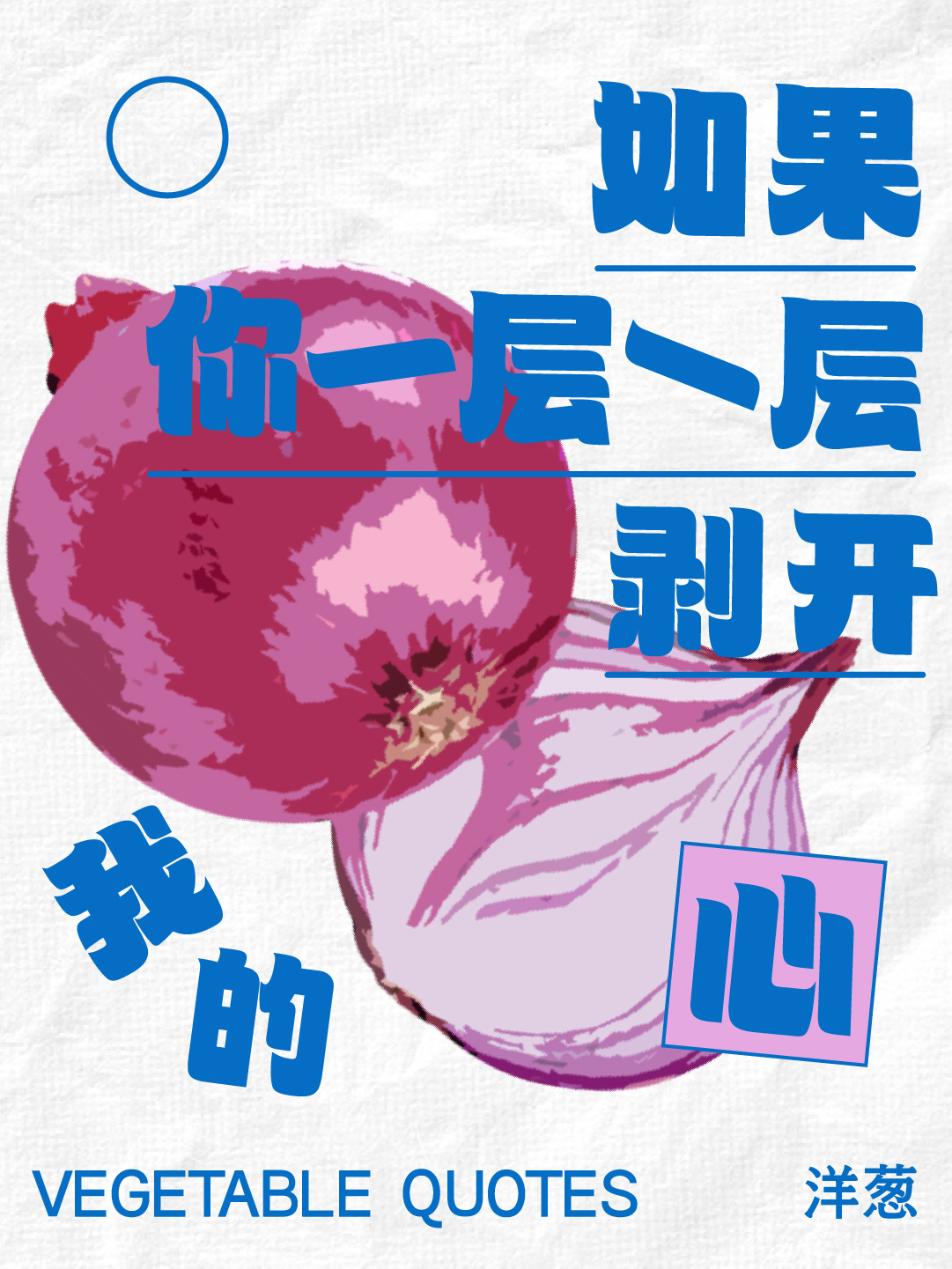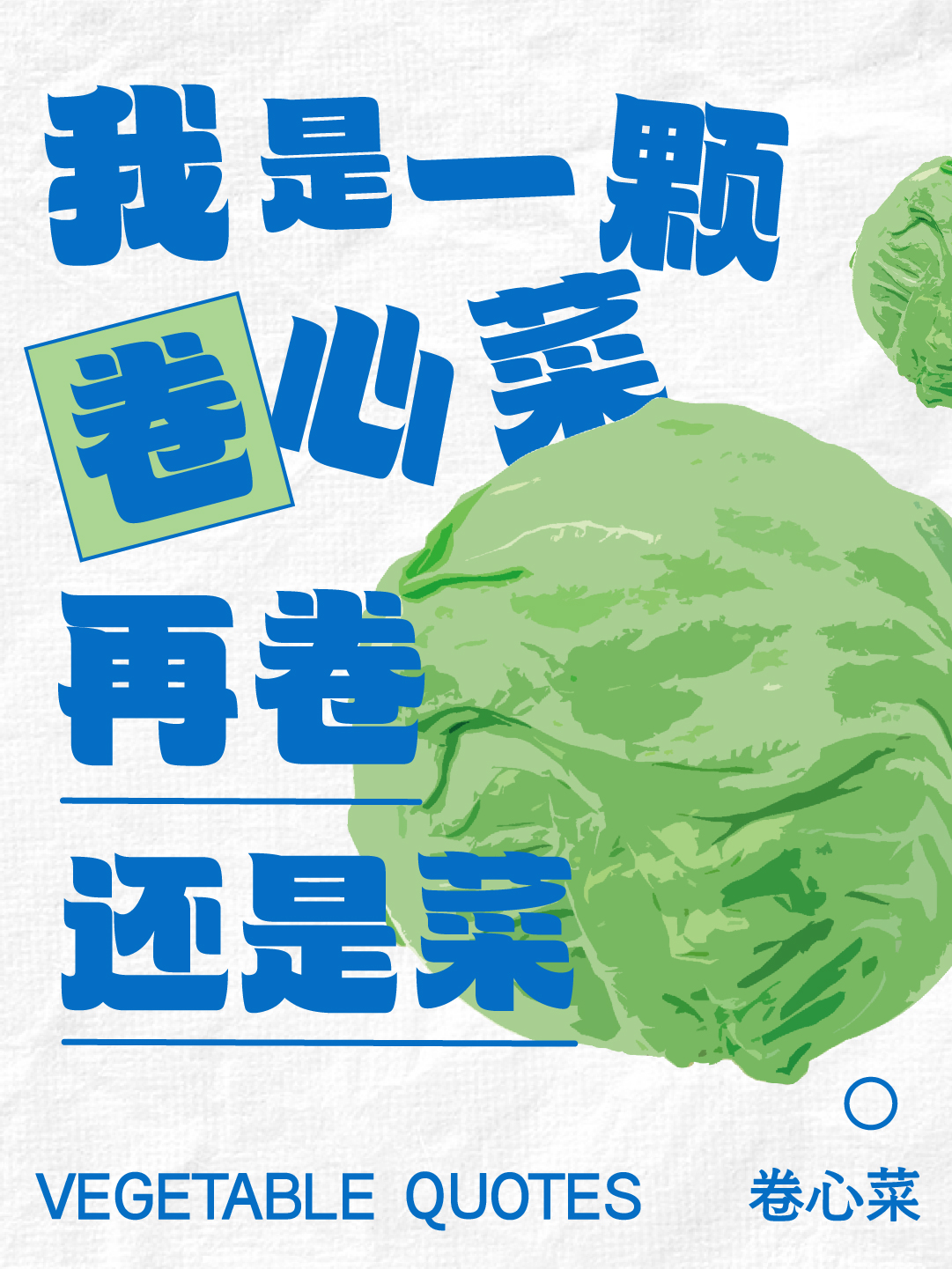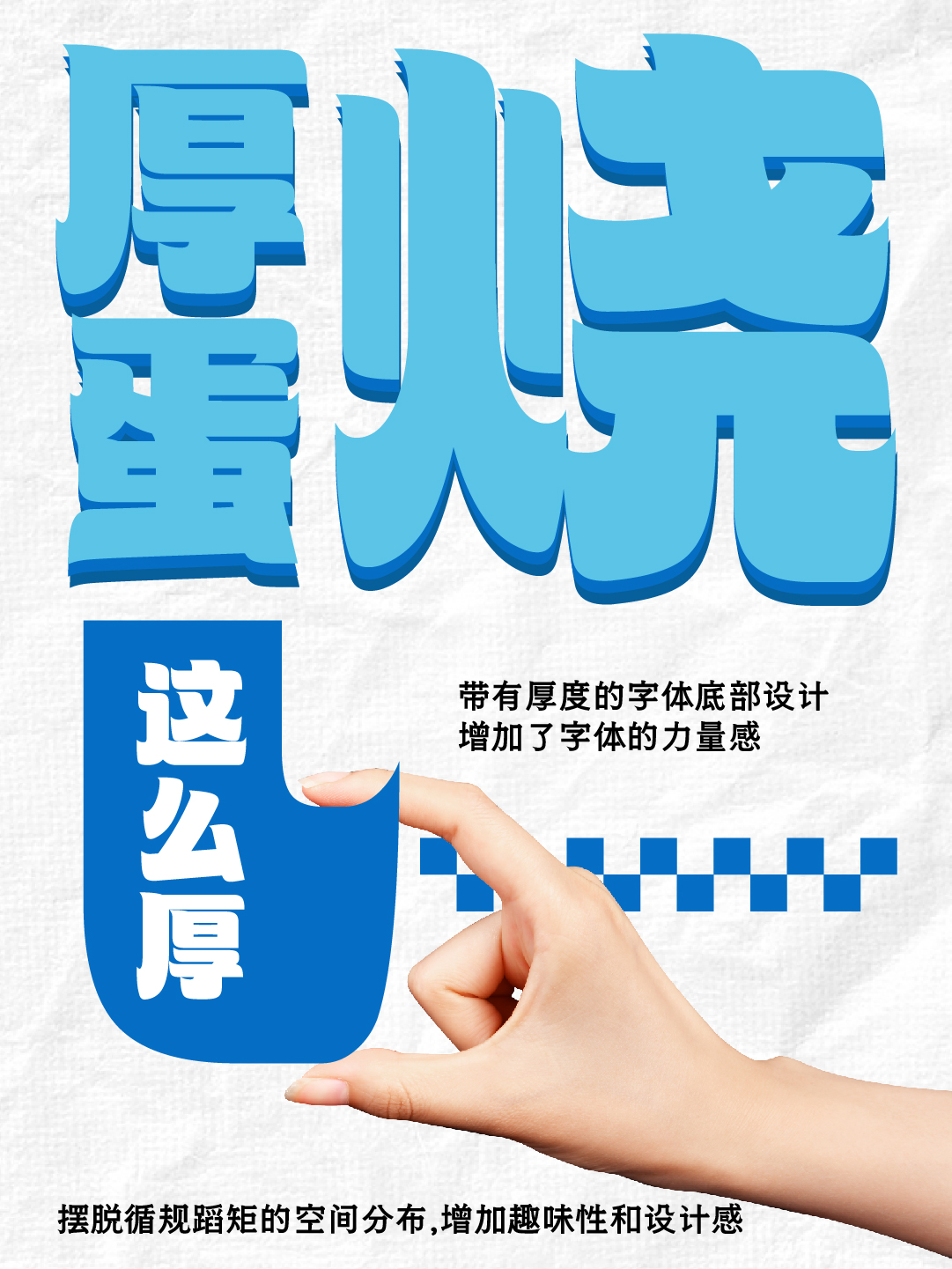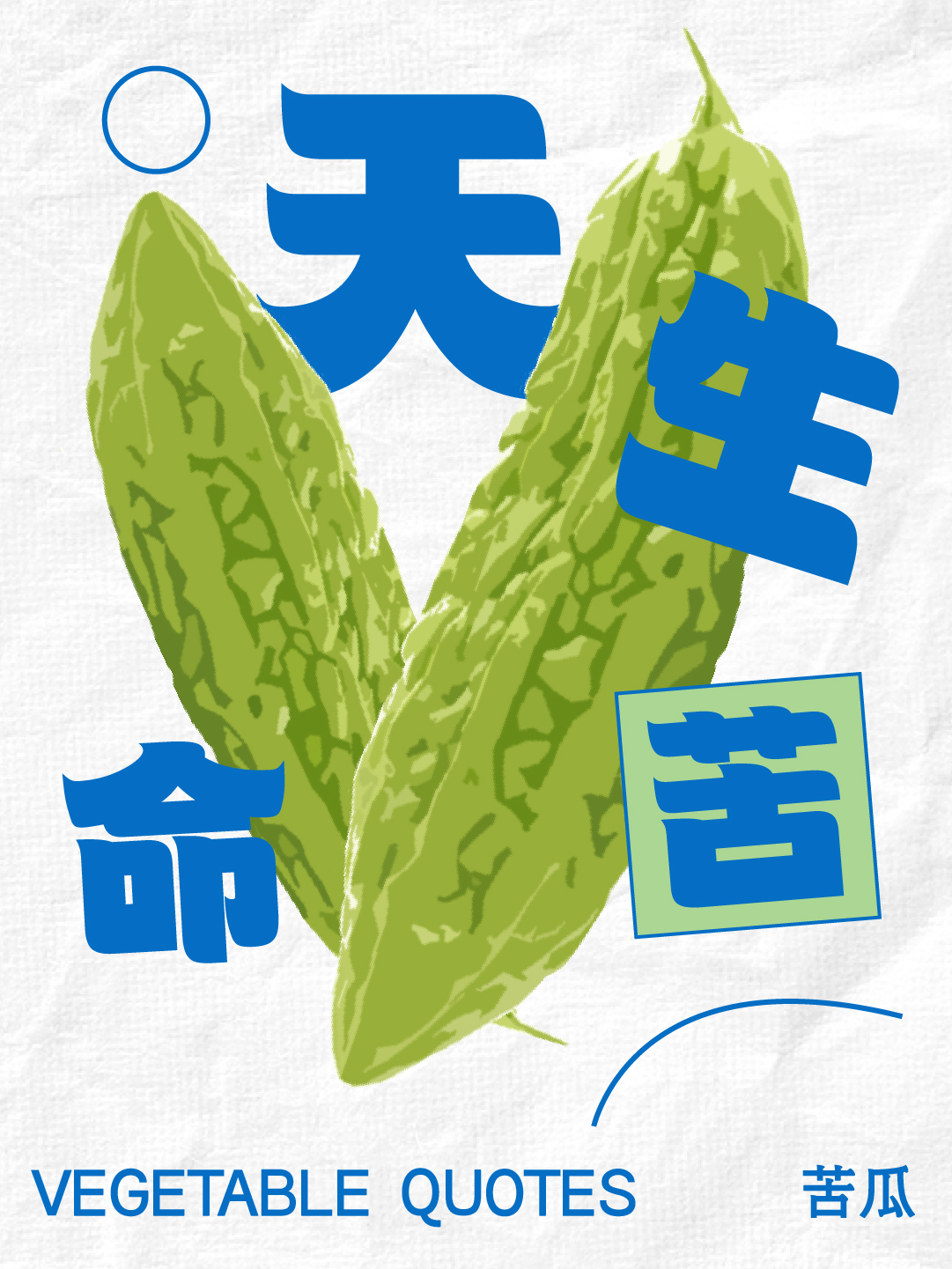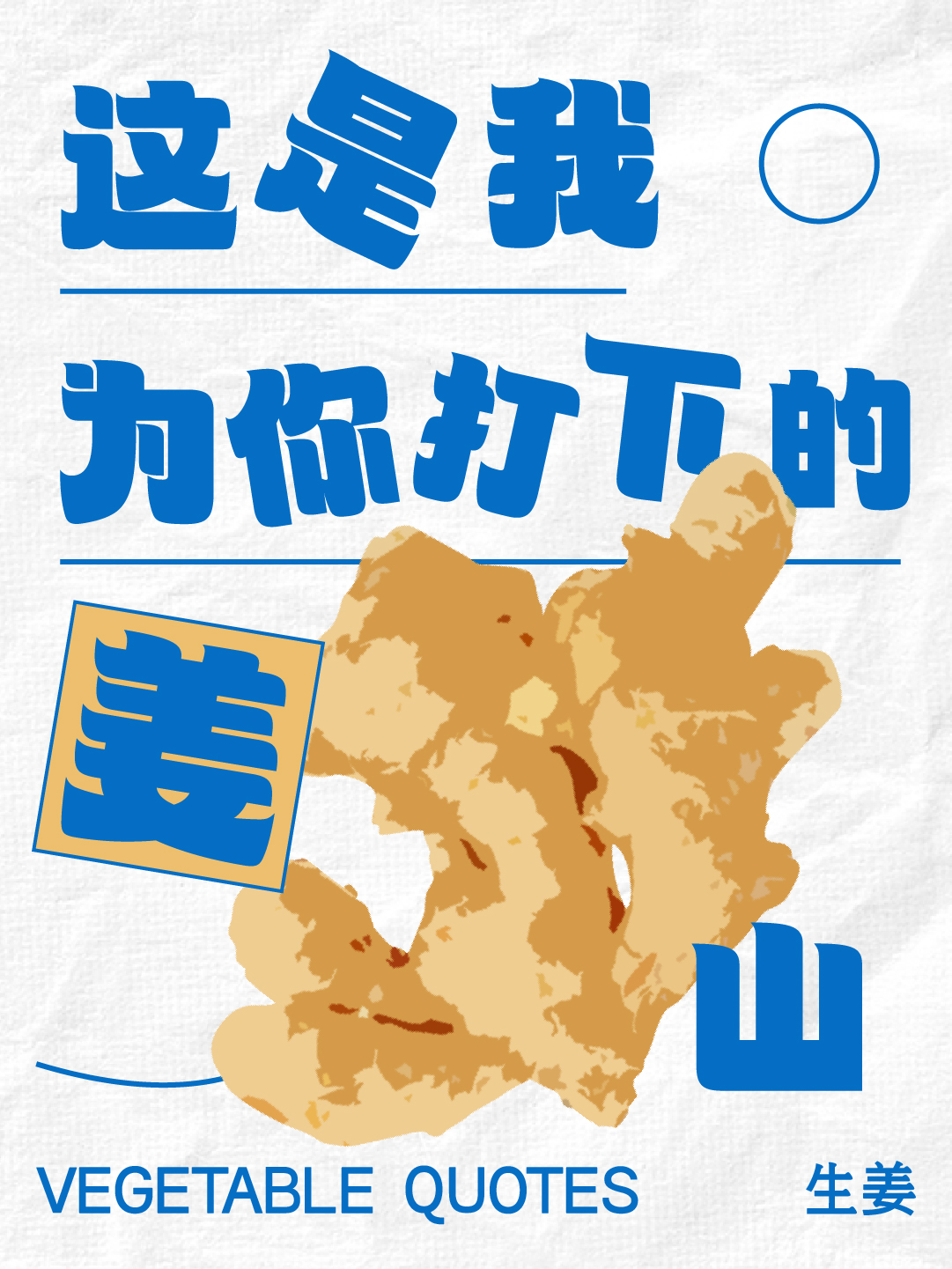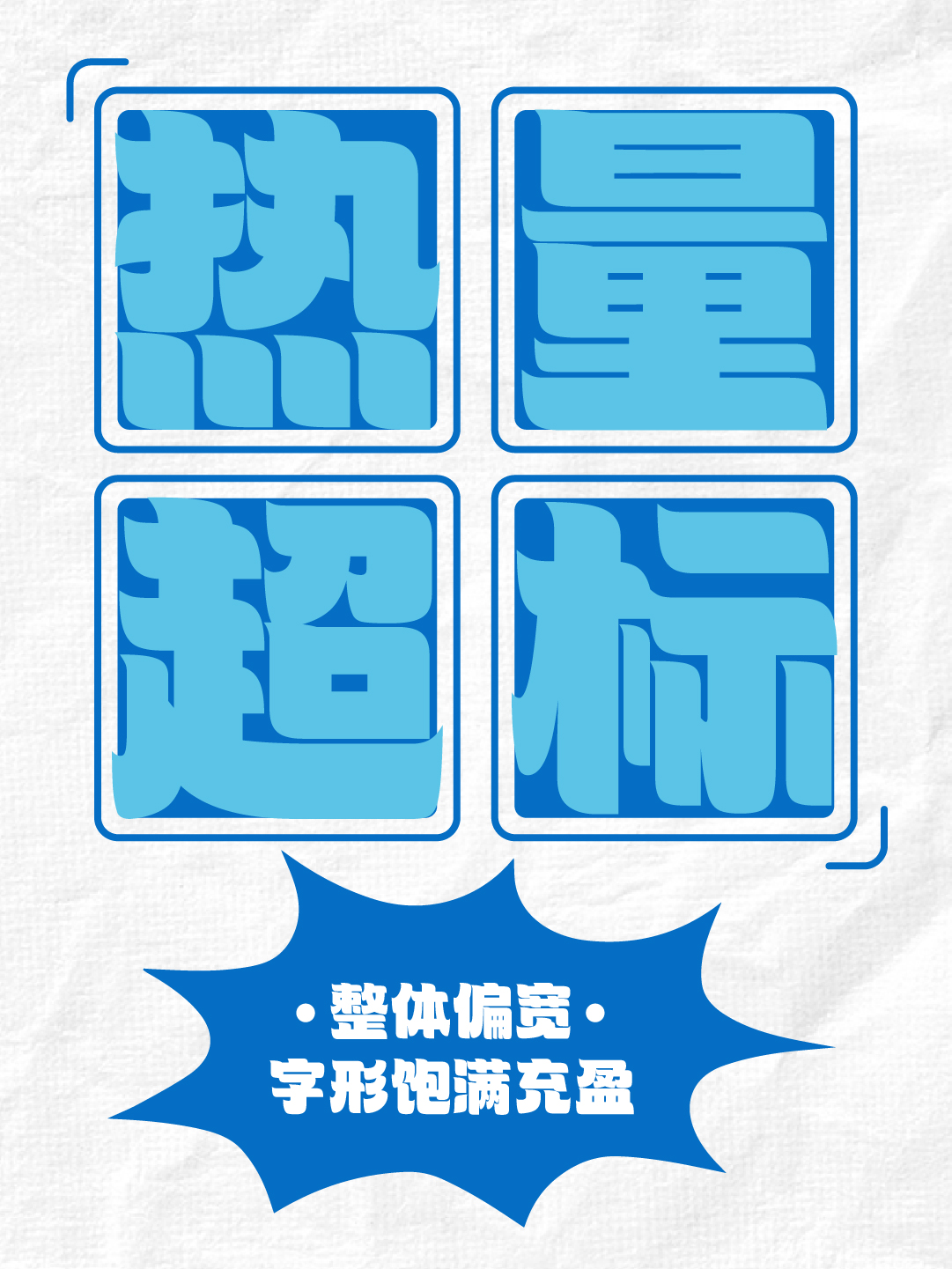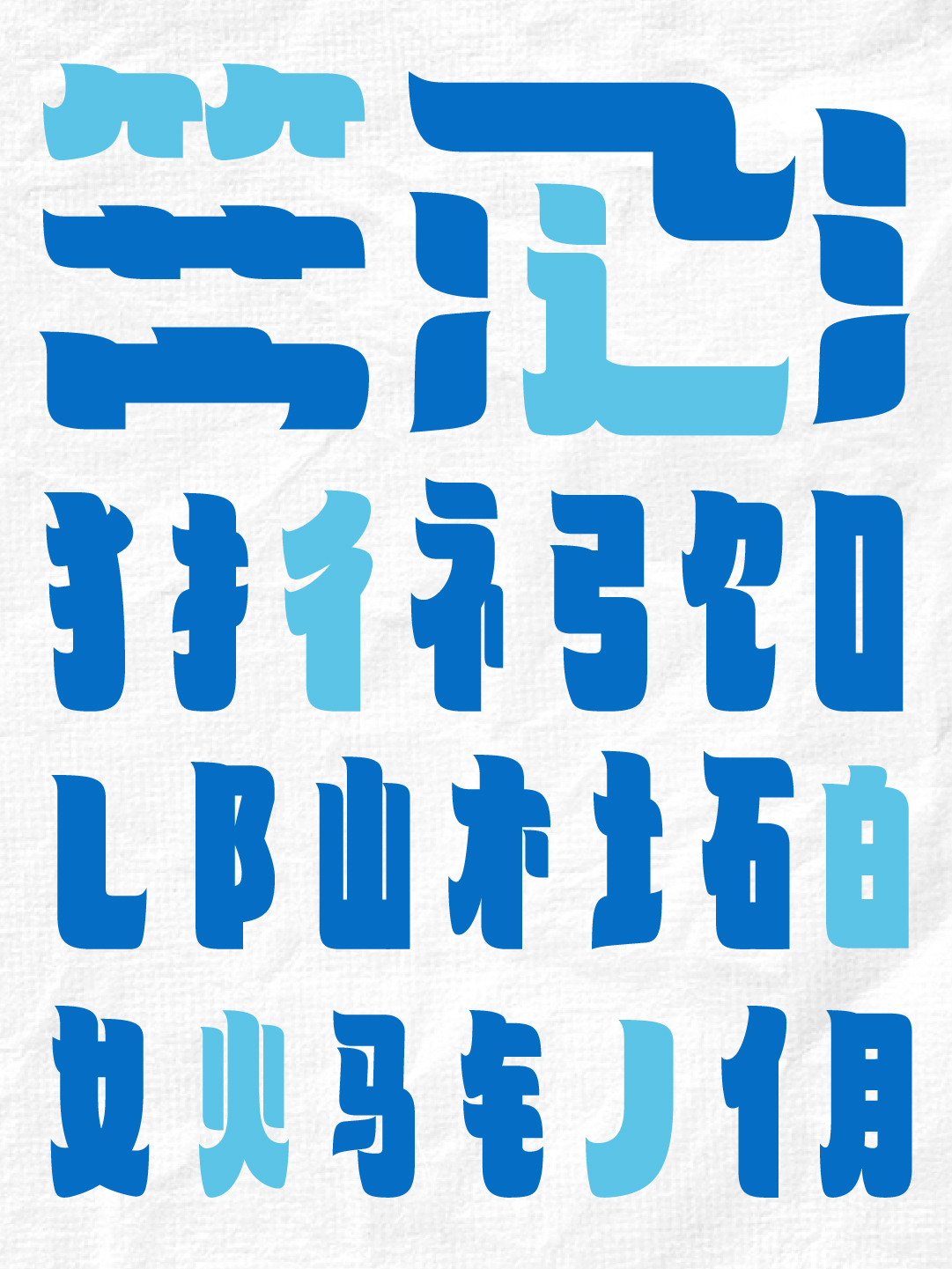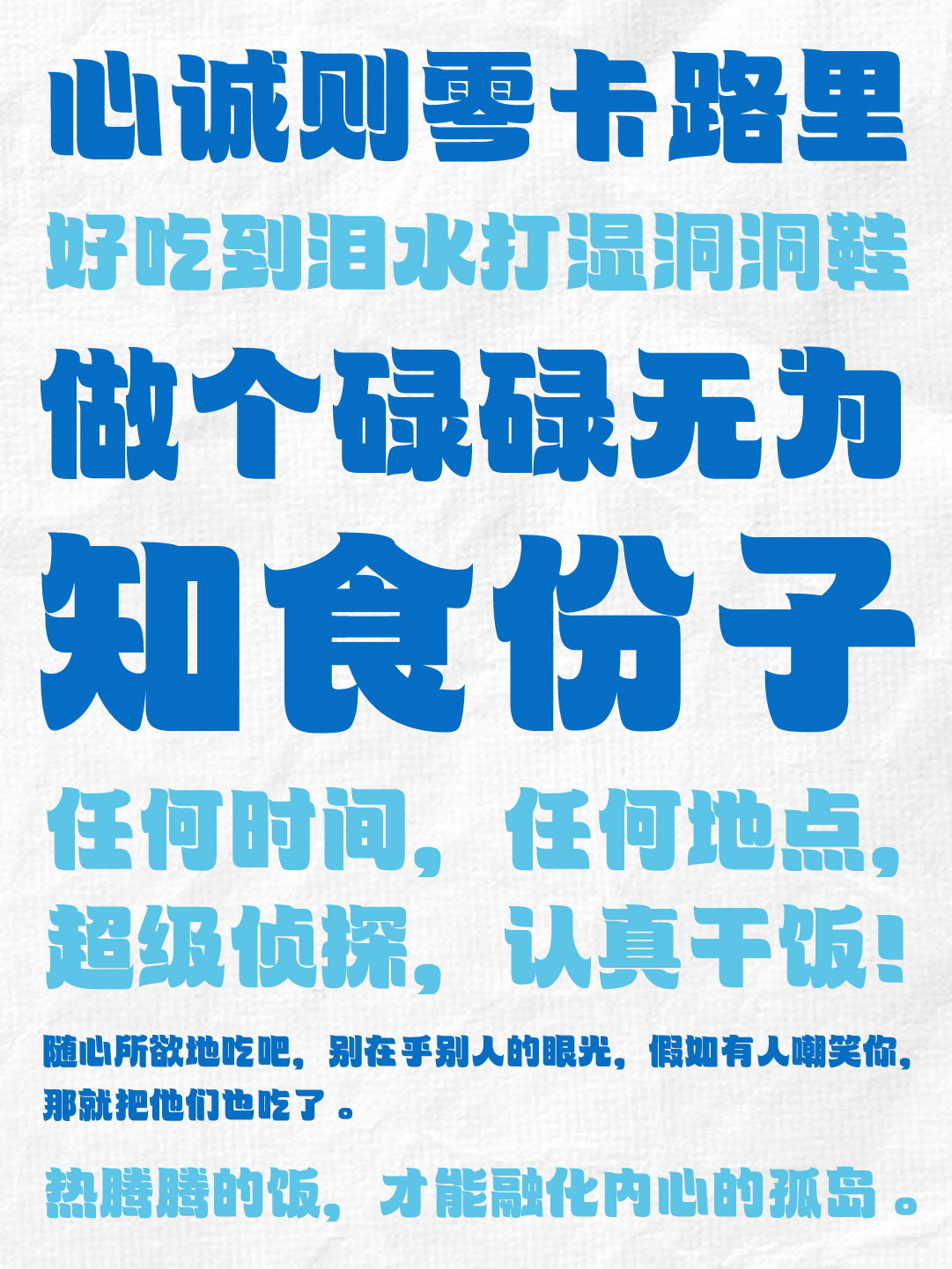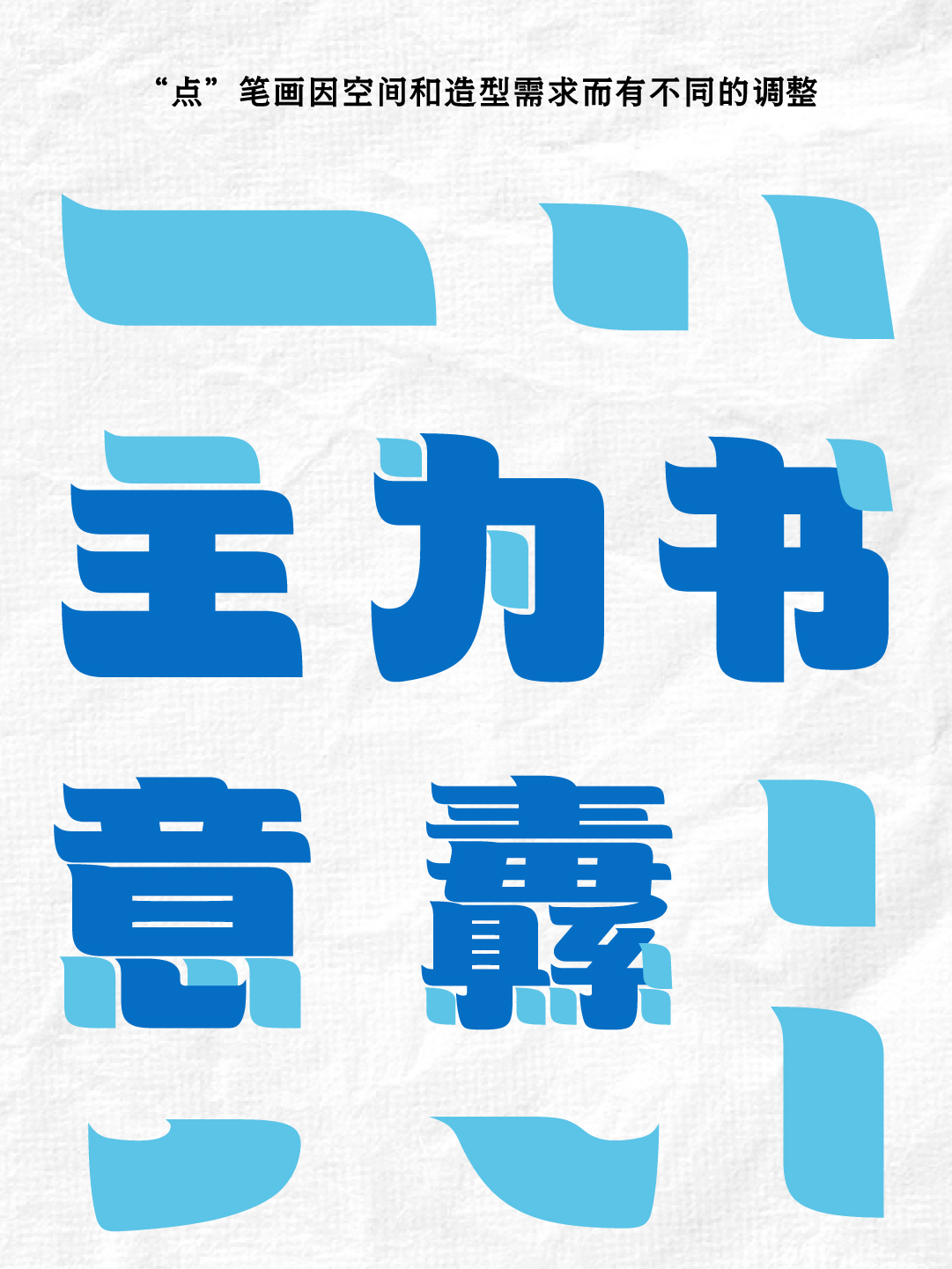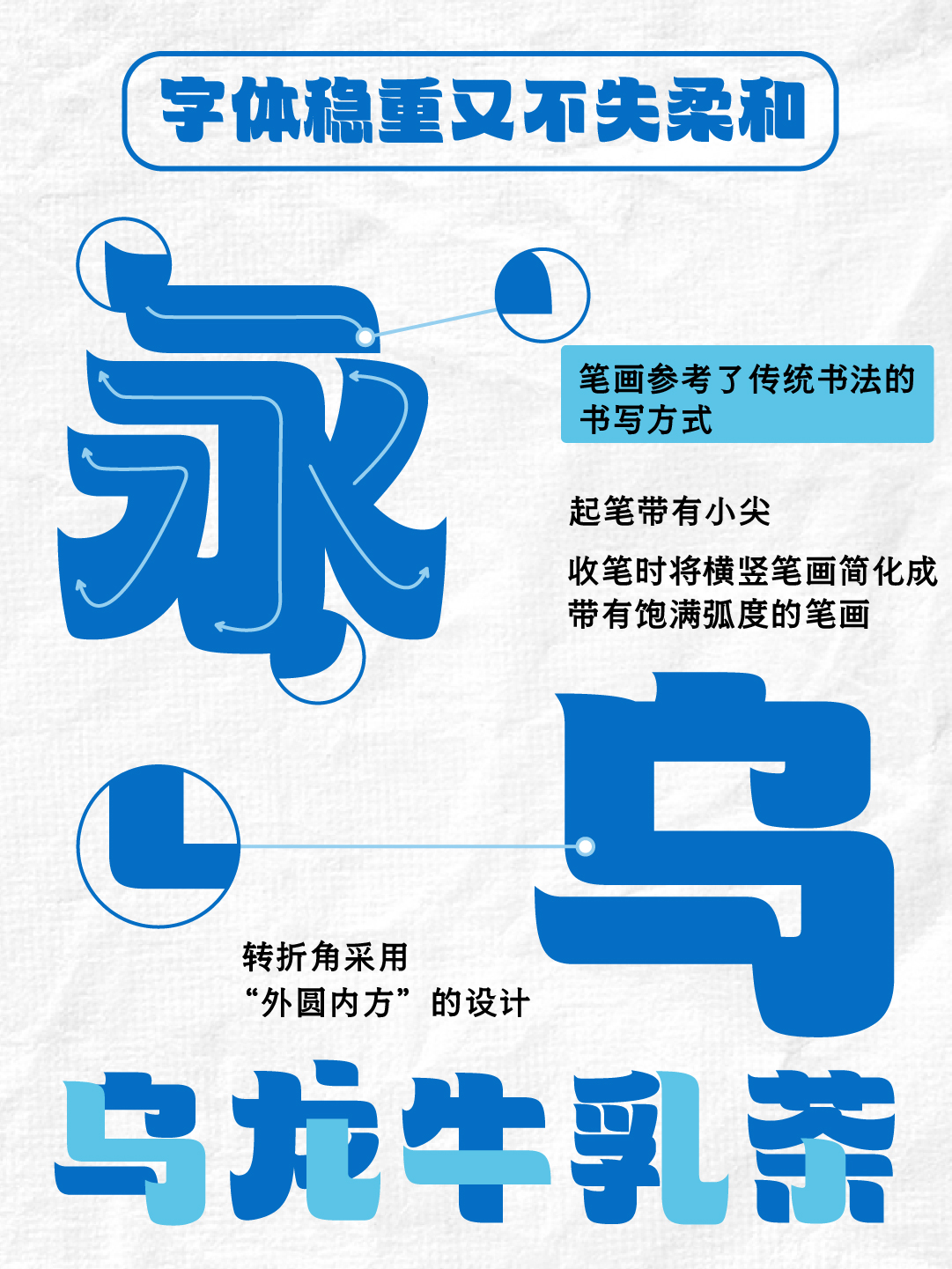
【字体创意溯源】
当烤好的舒芙蕾呈现在眼前,再大的烦恼似乎都能被抛诸脑后。这套“也字工厂舒芙蕾”字体,其起笔之处巧妙地带有“小尖”,恰似制作舒芙蕾时,将面糊缓缓挤出所形成的精致尖尖,灵动又充满趣味。正因如此,它既能成为各类美食海报上夺人眼球的标题字,为美食增添一份诱人的氛围;也能完美融入产品设计中,成为吸引目光的亮点,故而得名“也字工厂舒芙蕾”。
【字体独特魅力】
“也字工厂舒芙蕾”堪称一款存在感Max的黑体字。在设计中,它占据更多体积空间,让字体呈现出饱满立体的视觉效果,仿佛自带一种强大的气场。不仅如此,它在外形上稳重可靠,笔画间却又不失柔美,二者达到了恰到好处的取舍与平衡,赋予了字体超高的辨识度,让人一眼便能记住。
字型特征:字面高度统一,整体造型偏宽,字形饱满充盈,仿佛一个个充满活力的小方块。中宫较大,重心适中,给人一种稳定而不失灵动的感觉,无论是在何种场景下使用,都能保持良好的视觉平衡。
笔画特征:笔画的设计借鉴了传统书法的书写方式,起笔处的小尖犹如书法家挥毫泼墨时的起始一笔,充满韵味。收笔时,横竖笔画被巧妙地简化成带有饱满弧度的形态,既让字体显得稳重可靠,又不失柔和之美。笔画极粗,线条饱满,虽然字体空间留白较少,但丝毫不影响其清晰识读,反而增添了一份独特的厚重感。
特殊设计:字体底部带有一定的厚度,笔画极粗,给人一种沉稳扎实的感觉。点笔画则根据不同的字体结构进行精心调整,使得字体留白更加和谐统一,整体呈现出一种精致而有序的美感。
【应用多元场景】
作为醒目的标题字体,“也字工厂舒芙蕾”在包装、游戏、影视、综艺、广告、绘本以及logo标志等需要强力视觉效果的场景中,都能大放异彩。在包装上,它能瞬间吸引消费者的目光,提升产品的吸引力;在游戏和影视中,它能为画面增添一份独特的氛围;在综艺和广告里,它能成为吸引观众注意力的关键元素;在绘本中,它能与画面相得益彰,营造出温馨有趣的氛围;在logo标志设计中,它更是能展现出独特的品牌个性,让人过目难忘。